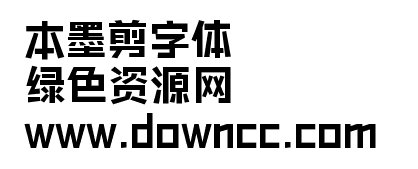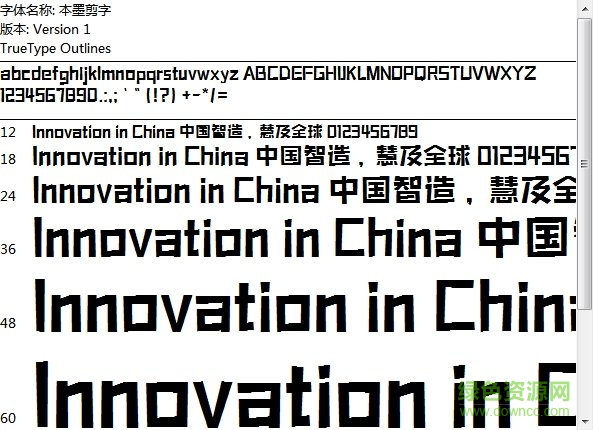
本墨剪字體是本墨字庫全新推出的一款剪紙?bào)w,字體厚重而端正,給人十分沉重的藝術(shù)字體體驗(yàn),自帶加粗和黑體,讓文字更加醒目,喜歡的朋友就來綠色資源網(wǎng)試試吧!
本字庫中文以國家GB2312-80標(biāo)準(zhǔn)設(shè)計(jì)制作,中文字?jǐn)?shù)6763個,另包含ASCII常用字符150個。
本墨剪體是本墨字體首款剪紙字體,帶給大家獨(dú)特的藝術(shù)審美,筆畫曲折如同裁剪不一,整體造型對稱,首尾呼應(yīng),可以廣泛運(yùn)用在藝術(shù)設(shè)計(jì)、海報(bào)設(shè)計(jì)、logo設(shè)計(jì)等諸多領(lǐng)域!